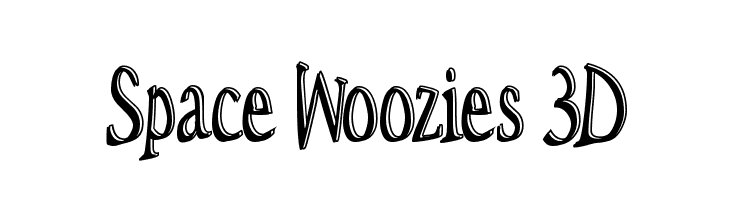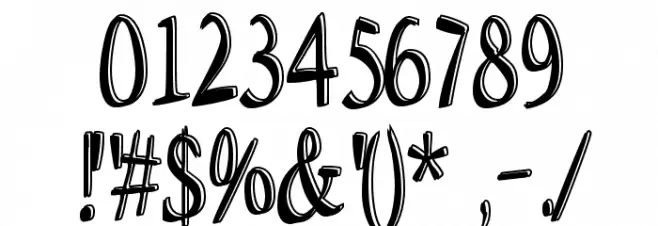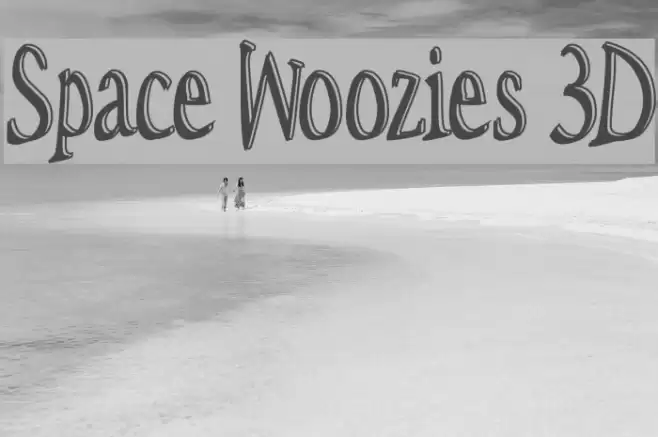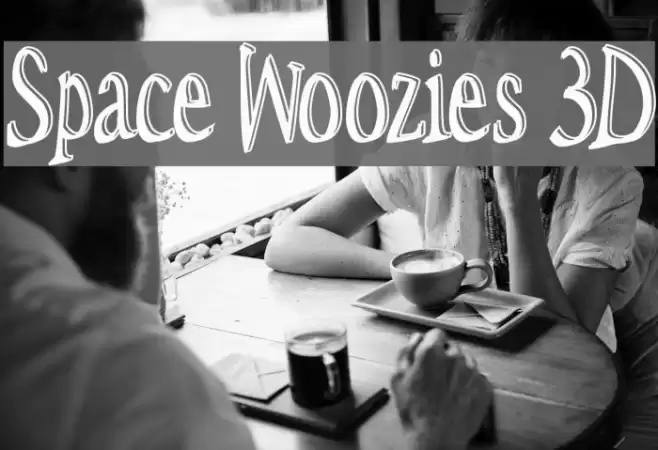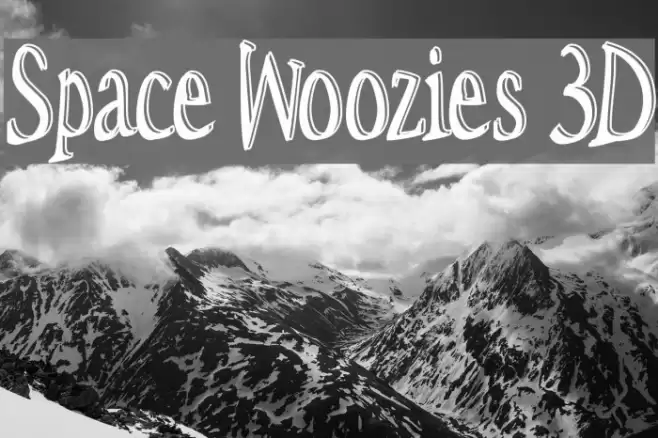
Space Woozies 3D Font
| Estilo general | Playful, Dynamic, Whimsical |
| Proyectos propuestos | Ideal for children's book covers, playful branding, posters, and creative digital content. |